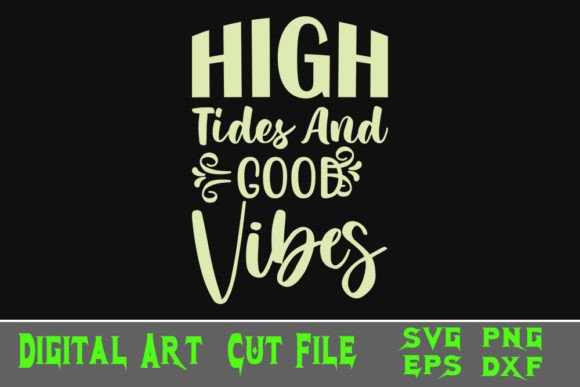
Beach Typhography SVG T-Shirt Design 7
Com Beach Typhography SVG T‑Shirt Design 7, você ganha um recurso premium que economiza tempo de produção e eleva o padrão visual da sua marca. Ideal para designers de moda, empreendedores de impressão sob demanda e amantes do estilo “beach vibe”. Não perca a oportunidade de adicionar este design ao seu catálogo e impulsionar as vendas nas próximas estações de verão.